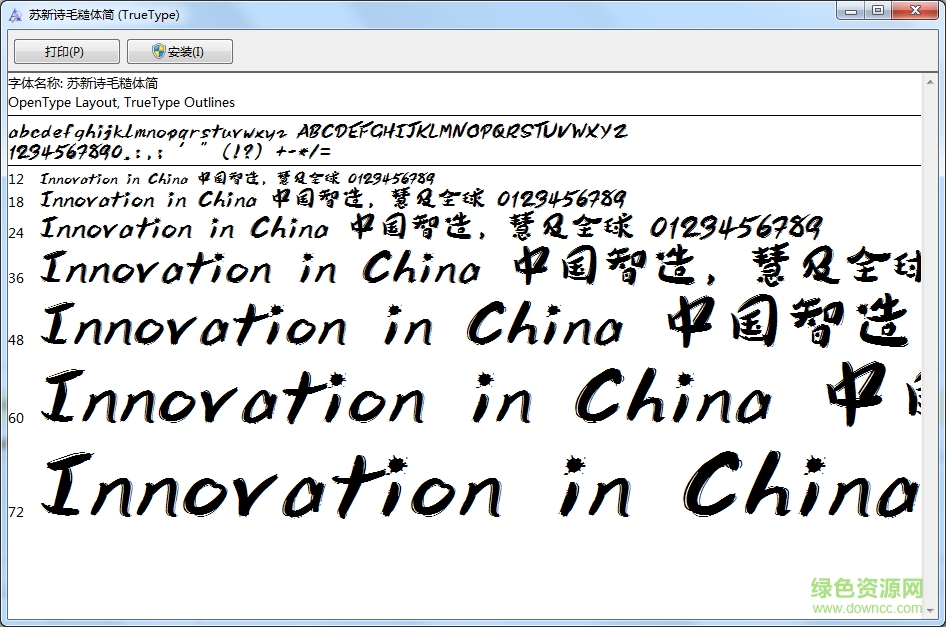
蘇新詩(shī)毛糙體簡(jiǎn)體是一款非常獨(dú)特的字體,文筆比較夸張和張揚(yáng),有點(diǎn)像寫(xiě)的歪歪斜斜的毛筆字,廣泛用于設(shè)計(jì)和廣告,歡迎有需要的朋友到綠色資源網(wǎng)下載體驗(yàn)!
蘇新詩(shī)毛糙體簡(jiǎn)字體是一款字形粗糙筆鋒犀利,應(yīng)用于書(shū)法方面的簡(jiǎn)體中文漢字字體。可用于卡通設(shè)計(jì)、廣告設(shè)計(jì)、平面設(shè)計(jì)、印刷包裝、報(bào)紙雜志等行業(yè)。